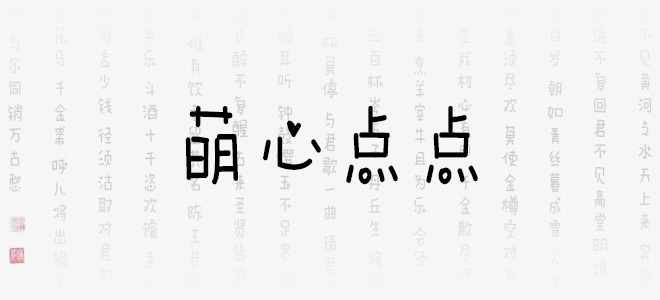
麥拉風(fēng)萌心點(diǎn)點(diǎn)字體是一款非??蓯?ài)的手寫(xiě)藝術(shù)字體,該字體給人第一印象就是可愛(ài)萌萌噠,其在字體的框架中加入大量的愛(ài)心圖案來(lái)裝飾,看上去極為美觀,適合應(yīng)用于藝術(shù)設(shè)計(jì)、平面宣傳設(shè)計(jì)、網(wǎng)頁(yè)設(shè)計(jì),書(shū)法字帖等領(lǐng)域,歡迎喜歡麥拉風(fēng)萌心點(diǎn)點(diǎn)字體的朋友前來(lái)下載使用。
麥拉風(fēng)萌心點(diǎn)點(diǎn)